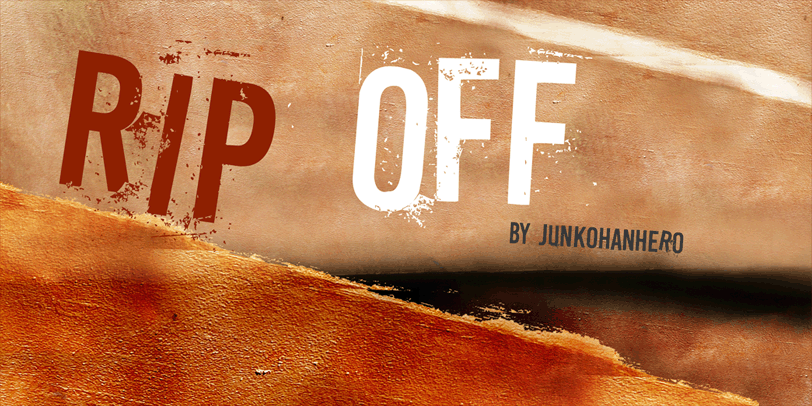
Aqui está a descrição conforme as instruções: Estamos entusiasmados por oferecer à você uma fonte artística chamada Rip-off Font, criada pelo designer Hamilton. Esta é uma excelente opção para projetos pessoais, pois está disponível de forma gratuita e sem restrições. Mas sabemos que muitas pessoas precisam usar esta fantástica fonte em trabalhos comerciais. Não há problema algum! Poderíamos fornecer um licenciamento comercial ao custo de 15 euros ou 20 dólares por meio do PayPal, com a opção de fazer uma doação regular se desejar. Para adquirir o licenciamento, basta enviar-nos esse valor através do PayPal. Depois disso, você só precisa nos escrever para confirmar que sua compra foi concluída. Uma maneira alternativa é usar nosso botão de doação, bem próximo ao botão de download da página. Não perca esta oportunidade de dar um toque único e diferenciado aos seus projetos comerciais usando Rip-off Font, uma fonte artística criada com carinho pelo designer Hamilton.